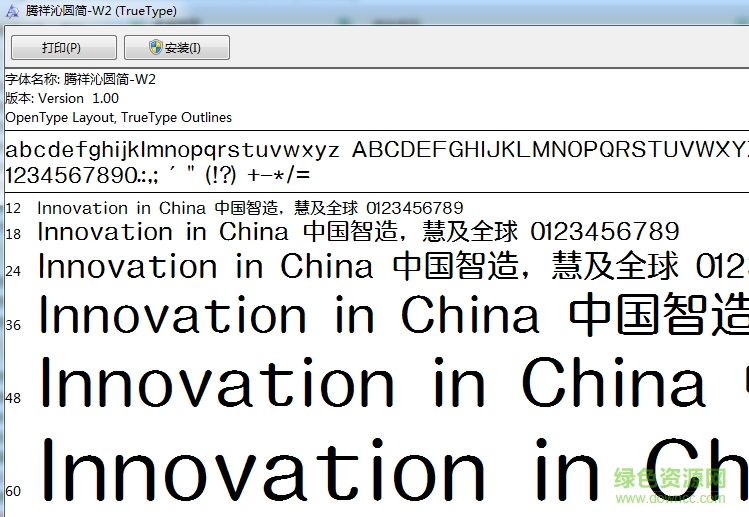
騰祥沁圓簡w2
騰祥沁圓簡w2字體騰祥字體庫中的一款簡體字體,該字體線條均勻,字型的整體效果也很出色,適用于各個設(shè)計領(lǐng)域。有需要的朋友就來綠色資源網(wǎng)下載吧!
騰祥沁圓簡w2字體是一款簡體中文字體,字體的字型十分出色,給人一種過目難忘的感覺,有需要的朋友就趕快來綠色資源網(wǎng)下載吧!